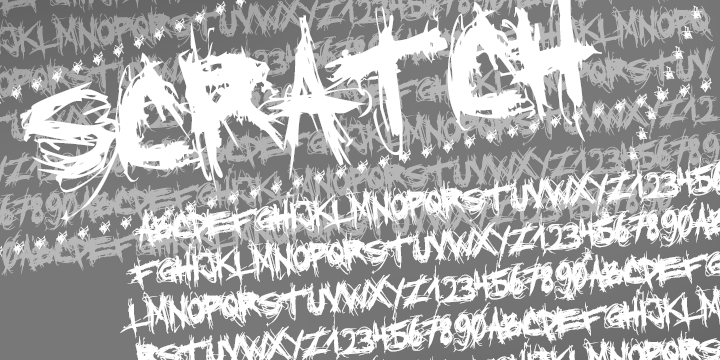
Шрифт кириллица рваный: Поцарапанные шрифты | Шрифты онлайн
Мы собрали 101 рукописный шрифт, который вы можете бесплатно использовать в любом дизайне. Задайте настроение бренда с помощью каллиграфии.
Рукописный шрифт — шрифт, созданный каллиграфом с помощью кисти, пера или специальных ручек. Обычно текст, написанный каллиграфическим шрифтом, выглядит более личным и душевным — как будто вы сами написали его от руки. Используйте его, чтобы вызвать доверие и добиться контакта с аудиторией.
Чтобы вы выбрали шрифт, который расскажет о вашем деле все, мы собрали 101 каллиграфический шрифт со свободной лицензией: их можно использовать и в личных целях, и в коммерческих проектах.
Бесплатные рукописные шрифтыРусские рукописные шрифты1. CelestinaЭтот рукописный шрифт кажется бодрым и веселым благодаря разной высоте «скачущих» букв. Читается трудно, поэтому не используйте Celestina на длинных текстах.
Celestina от Antonina Zhulkova2. AleksandraCНа мягкие скругленные буквы приятно смотреть, и именно эта округлость превращает обычный гротеск в очаровательный декоративный шрифт. Попробуйте его, если хотите создать ощущение уюта.
AleksandraC от Александра Шевчука3. Brush font oneВыразительный шрифт с угловатыми буквами. Подойдет, когда нужно создать эффект написанного вручную текста.
Brush font one от Aba Sh4. AlexanderКлассический каллиграфический шрифт для официальных документов и деловых бумаг.
Alexander от George Douros5. АркадияАскетичный и сдержанный шрифт. Если бы не аккуратные петли, его сложно было бы отличить от обычного гротеска.
Аркадия от Igor Kosinsky6.
Пара из каллиграфических шрифтов толстой кистью. Подойдет для детских или женских брендов.
Elowen от Кати Язвинской7. SlimamifВ одной упаковке — четыре начертания разной толщины (light, regular, medium, bold) и все самые распространенные знаки.
Slimamif от Dmitri Zdorov8. Le murmureИзначально шрифт был создан в Париже для фирменного стиля студии Murmure. Позже чешский шрифтовик Алекс Слобженинов адаптировал его к кириллице — и теперь он привлечет внимание к любому молодежному и творческому бренду.
Le murmure от Jérémy Landes, Alex Slobzheninov9. MolodostКак удалось объединить мотивы из древнерусских рукописных книг и «разложение» цвета в современном мониторе — загадка, но получилось дерзко. Миллениалы оценят.
Molodost от Alexey Atapin10. Sprite GraffitiОбъемные буквы этого шрифта хорошо подойдут для блога о хип-хопе или скейтбординге, для принтов на майках и любого другого андеграунда. Йоу 🙂
Sprite Graffiti от Jelio Dimitrov — Arsek, Georgi Dimitrov — Erase11. Serifiqo 4FПетли делают любой шрифт женственнее, а тонкие засечки придают элегантности. Serifiqo подойдет только для заголовков, потому что строчные в нем не отличаются от прописных — читать длинный текст в таком шрифте сложно.
Serifiqo 4F от Sergiy Tkachenko12. Good Vibes ProСамо название намекает на личный дневник, фотоальбом, приглашение на торжество — все это можно оформить с помощью такого шрифта.
Good Vibes Pro от Robert E. Leuschke, Andrey V. Markelov13. Paint-it-BlackНеимоверно красивый альбом из шрифтов с историей. Этот — про древних славян и их таинственную мифологию, но в наборе есть и огонь, и переплетенные корни деревьев — всего 5 кардинально разных шрифтов.
Paint-it-Black от Plamen Motev, Svet Simov14.
Мечтательный, легкий и… страшно неразборчивый! Найдите в этом наборе первую букву из названия бренда — и сделайте из нее логотип. Получится что-то загадочное и первобытное.
Jelani от Ekaterina Chernyshova aka chekart15. TsarevichПекарни и рестораны национальной кухни, сувенирные магазинчики — этот качественный и продуманный каллиграфический шрифт для вас.
Tsarevich от Misha Panfilov16. БерезкиЕще один шрифт Миши Панфилова в нашей подборке. Вытянутые буквы, «нацарапанные» с легкой небрежностью, подойдут неформальному бизнесу — как на вывеске, так и в вебе.
Березки от Misha Panfilov17. MADE LikesВ наборе сразу два шрифта — один с засечками, другой рукописный. Поэтому искать шрифтовую пару самому не придется.
MADE Likes от MADE Type18. DenistinaСложный шрифт, который подойдет не всем. Посмотрите, какой разный наклон у букв и как закручена, например, английская s (да, латиница в наборе тоже есть) — если использовать не в меру, то будет выглядеть неаккуратно.
Denistina от Christina Larina19. TangakНеформальный шрифт для айдентики кафе или бара.